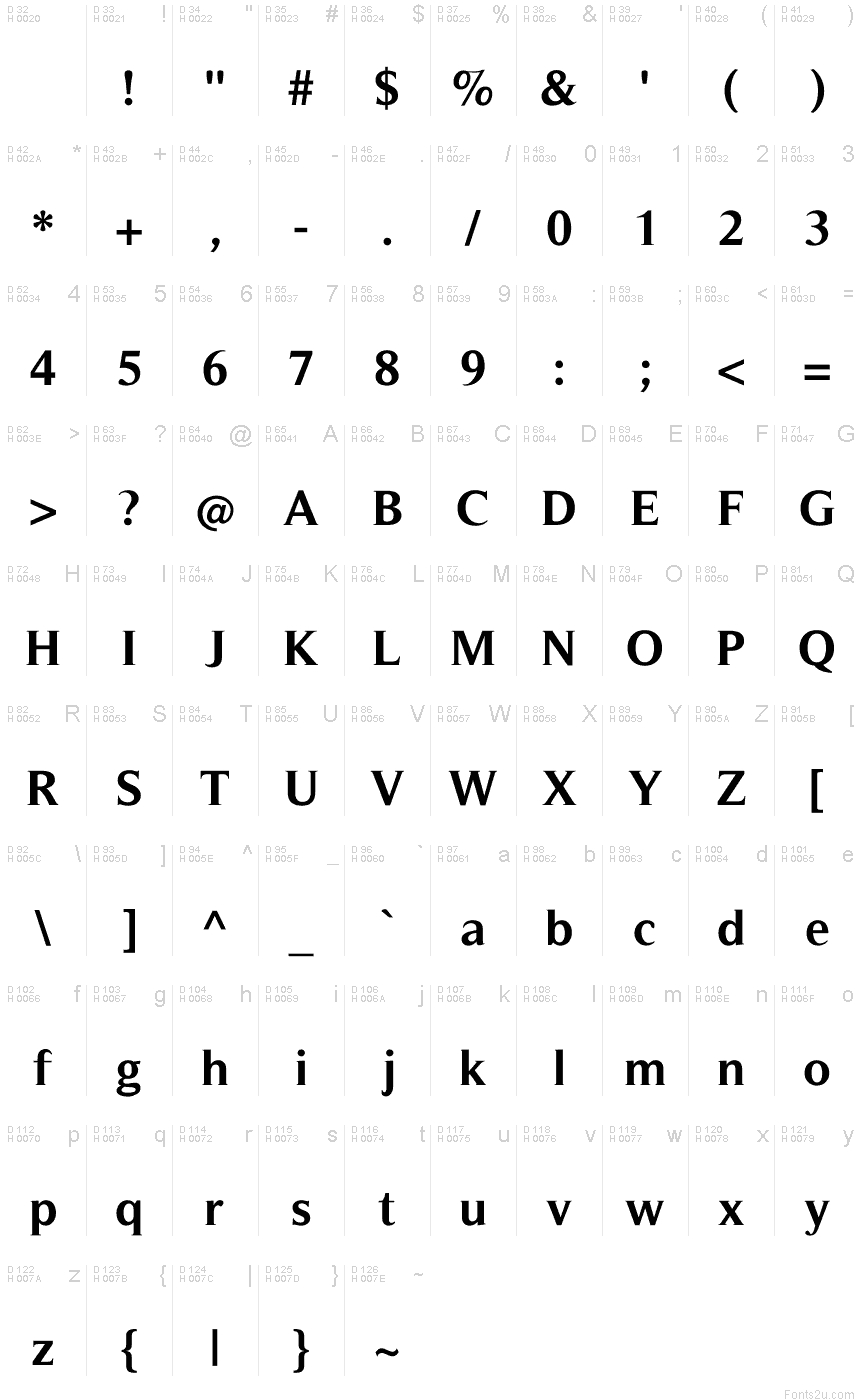
Timeless-Bold
Timeless Bold autorstwa M. Kleina z Fonteria to darmowy, klasyczny krój szeryfowy o spokojnym, literackim charakterze. Litery nawiązują do tradycyjnej typografii książkowej: z wyraźnym pionowym akcentem, ostrymi, wspornikowymi szeryfami i czytelnymi minuskułami, które nadają krojowi stały, znajomy rytm, unikając przy tym kruchości czy nadmiernej dekoracyjności.
Sprawdza się w nagłówkach redakcyjnych, na okładkach książek, zaproszeniach, grafikach muzealnych i opakowaniach, gdzie darmowy font musi brzmieć kulturalnie, nie stając się przy tym zbyt skomplikowanym. Solidna waga i oldschoolowy klimat czynią go naturalnym wyborem do krótkich nagłówków, rozpoczynania rozdziałów czy kart tytułowych, zwłaszcza gdy szukasz czegoś formalnego, co jednocześnie zachowuje ciepły wyraz.